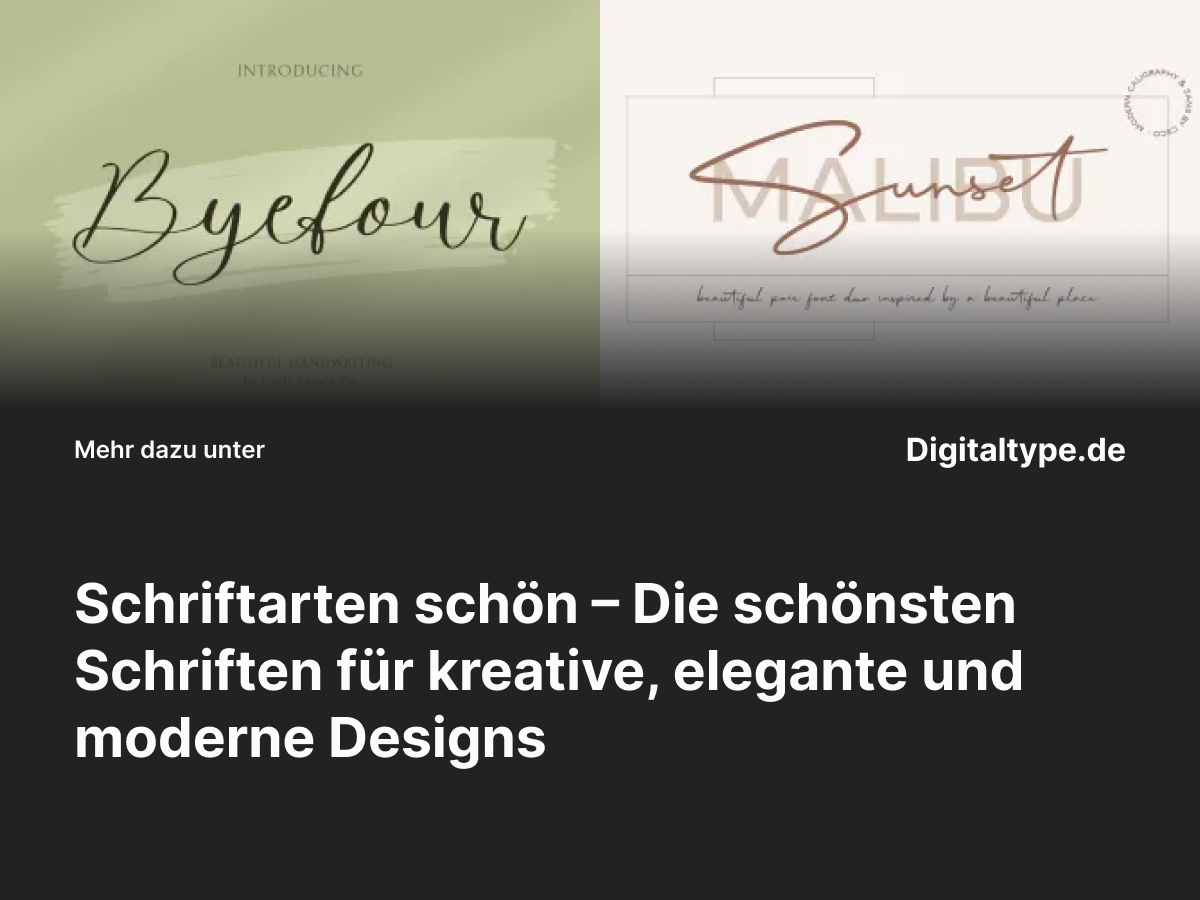
Eine schöne Schriftart kann Emotionen wecken, Stimmungen transportieren und einem Design sofort Charakter verleihen. Ob du ein Logo entwirfst, eine Einladung gestaltest oder Social-Media-Grafiken erstellst – schöne Schriftarten machen den Unterschied zwischen „gut“ und „unvergesslich“. In diesem Artikel zeigen wir dir, was schöne Schriften ausmacht, wie du sie gezielt einsetzt und welche 6 Font-Empfehlungen deinem Design mehr Stil und Persönlichkeit geben.
Was macht eine schöne Schriftart aus?
Schönheit in der Typografie ist subjektiv – sie hängt von Kontext, Stilrichtung und Emotion ab. Dennoch gibt es gemeinsame Merkmale, die schöne Schriftarten definieren: harmonische Proportionen, ausgewogene Linien, gute Lesbarkeit und ein ästhetisches Schriftbild. Manche Schriften sind elegant und fein, andere charmant handgezeichnet oder modern und minimalistisch.
Designer wählen schöne Fonts, um Gefühle zu vermitteln – Liebe, Luxus, Freude oder Kreativität. Besonders in Mode-, Lifestyle- und Hochzeitsdesigns spielen sie eine zentrale Rolle, da sie Botschaften mit Emotion verstärken.
Wann du schöne Schriftarten verwenden solltest
- ✔️ Für Logos und Marken, die Eleganz oder Persönlichkeit ausdrücken möchten.
- ✔️ In Hochzeitseinladungen, Grußkarten oder Save-the-Date-Designs.
- ✔️ Für Zitate, Social-Media-Posts oder Editorial-Projekte mit emotionalem Bezug.
- ✔️ Wenn du deinem Design eine hochwertige, stilvolle Note verleihen möchtest.
Eine schöne Schriftart kann minimalistischen Layouts Leben einhauchen oder verspielten Designs Harmonie verleihen. Sie ist das Herzstück visueller Kommunikation.
Die 6 schönsten Schriftarten für elegante Designs
Hier findest du sechs sorgfältig ausgewählte Schriftalternativen, die Schönheit, Balance und Ausdruck perfekt verbinden. Ob handgeschrieben, klassisch oder modern – jede dieser Fonts bringt ihren eigenen Charme mit.
1. Byefour Beautiful Script
Byefour ist eine elegante Script-Schrift mit fließenden Linien und natürlicher Handwriting-Ästhetik. Sie eignet sich hervorragend für Einladungen, Branding und Social-Media-Grafiken. Ihre sanfte Dynamik vermittelt Romantik und Leichtigkeit – perfekt für feminine oder kreative Designs.
2. Malibu Sunset – A Beautiful Font Duo
Dieses Font-Duo kombiniert eine moderne Sans Serif mit einer wunderschönen Script-Schrift. Gemeinsam schaffen sie Balance zwischen Klarheit und Emotion. Ideal für Branding, Editorials oder Lifestyle-Marken, die modern, aber warm wirken möchten.
3. CS Michigan Handwritten Font
CS Michigan bringt natürliche Handwriting-Energie ins Design. Sie wirkt freundlich, authentisch und künstlerisch. Eine perfekte schöne Schriftart für persönliche Projekte, Lifestyle-Content oder Produktverpackungen mit individueller Note.
4. CS Megara Handwritten Script Font
CS Megara ist elegant, weich und raffiniert. Mit ihren feinen Kurven und harmonischen Buchstabenformen ist sie ideal für Hochzeitseinladungen, Beauty-Branding oder kreative Zitate. Ihre Balance aus Natürlichkeit und Luxus macht sie vielseitig einsetzbar.
5. CS Rottage Classic Serif Font
CS Rottage ist eine klassische Serifenschrift mit elegantem Charakter. Sie vermittelt Tradition und Qualität – ideal für Editorials, Logos oder Verpackungsdesigns. Diese schöne Schriftart eignet sich besonders für Projekte mit einem Hauch Vintage und Stilbewusstsein.
6. Chavler Disco
Chavler Disco ist eine moderne, verspielte Schrift mit Retro-Charme. Sie kombiniert lebendige Formen mit künstlerischem Ausdruck und eignet sich hervorragend für kreative Poster, Musik-Events oder auffällige Social-Media-Designs. Ein Must-have für mutige Designer.
Design-Tipps für schöne Schriftarten
- 1. Weniger ist mehr: Verwende maximal zwei Schriftarten pro Design, um visuelle Harmonie zu bewahren.
- 2. Achte auf Kontrast: Kombiniere eine verspielte Script-Schrift mit einer klaren Sans Serif für Balance.
- 3. Experimentiere mit Farben: Pastelltöne oder warme Metallics betonen den ästhetischen Charakter schöner Fonts.
- 4. Beachte den Kontext: Eine schöne Schrift wirkt in minimalistischen Layouts stärker als in überladenen Designs.
Fazit: Schöne Schriftarten mit Stil und Emotion
Eine schöne Schriftart ist weit mehr als Dekoration – sie ist Emotion, Charakter und Markenbotschaft in einem. Ob handgeschrieben, elegant oder modern: Mit der richtigen Schrift bringst du Persönlichkeit in jedes Projekt.
Die vorgestellten Fonts vereinen Stil, Balance und Vielseitigkeit. Egal, ob du ein Branding entwickelst, Einladungen gestaltest oder kreative Inhalte veröffentlichst – diese schönen Schriftarten verleihen deinem Design das gewisse Etwas.